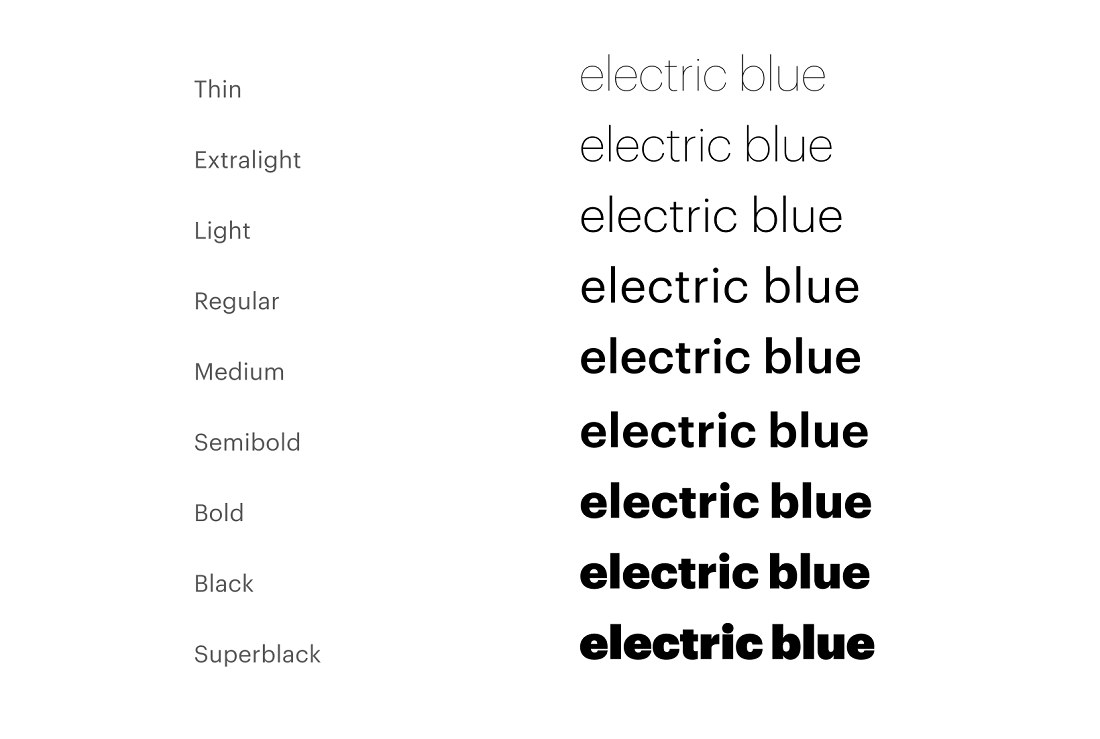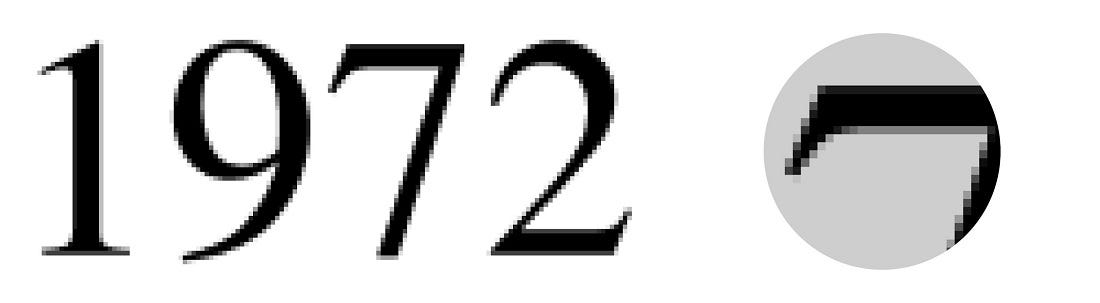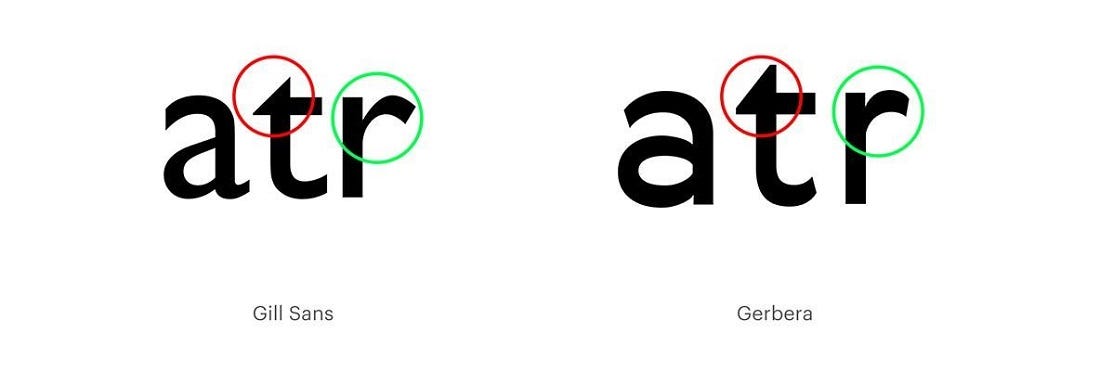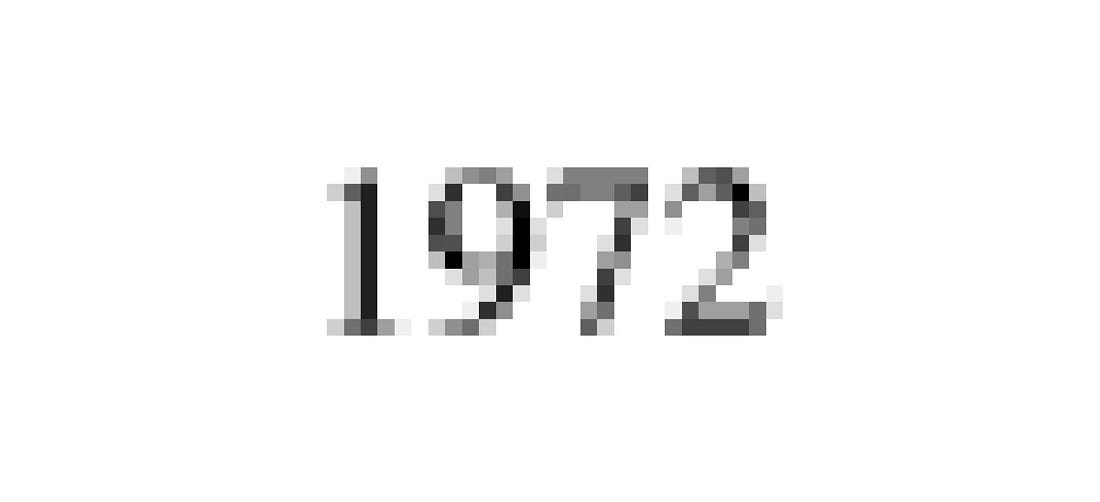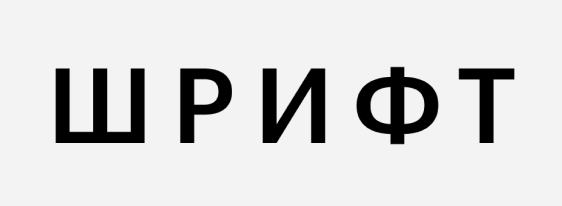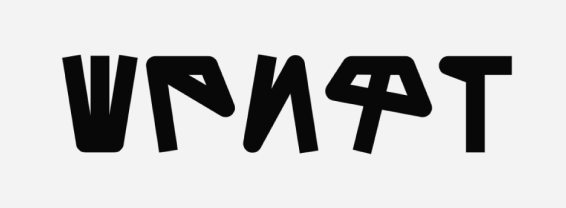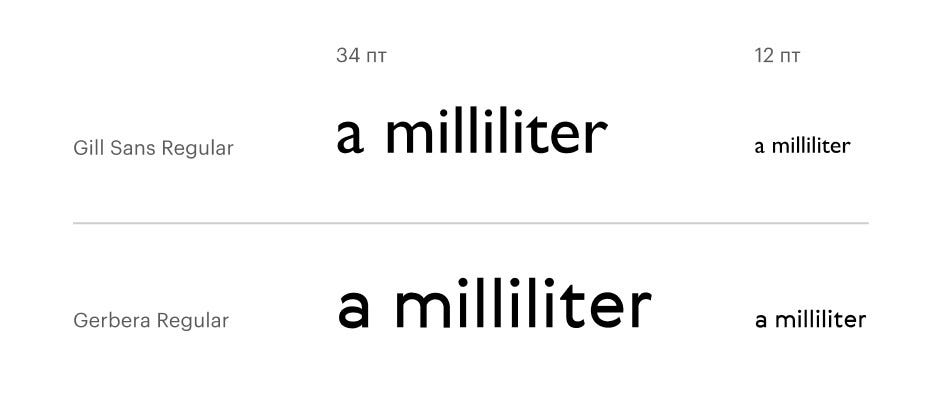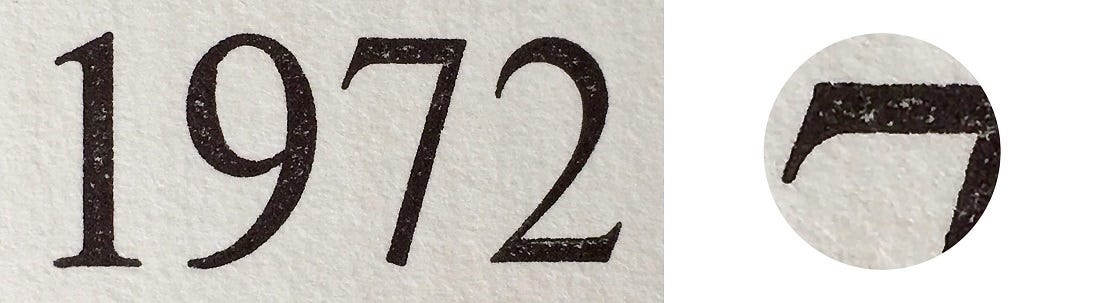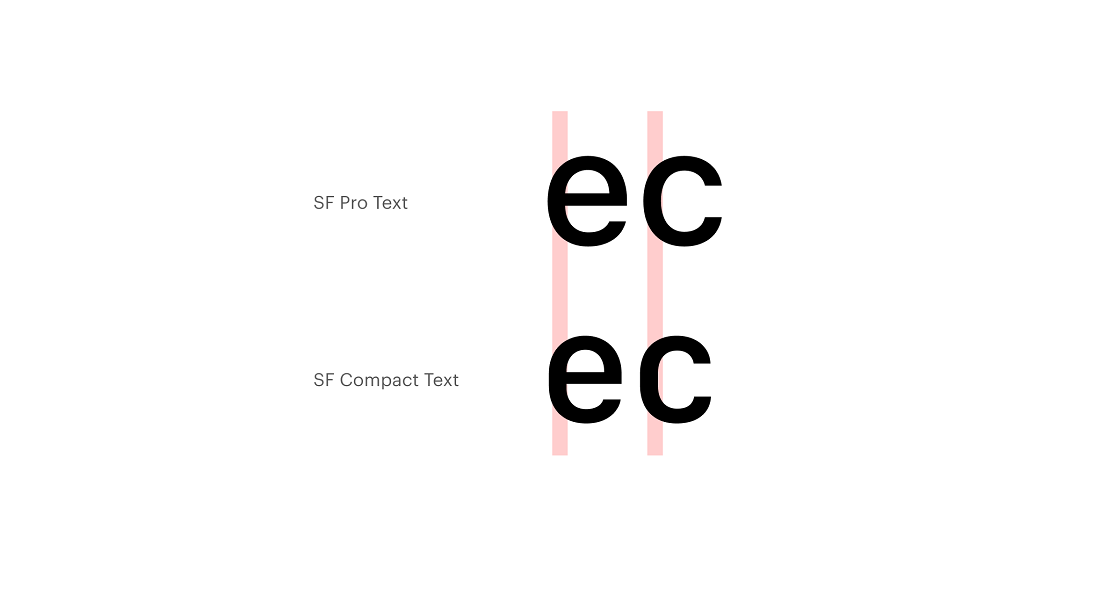
Как правильно выбрать шрифт для диджитал
Шрифт — это удивительное изобретение человека. Являясь, по сути, рисунком букв и знаков, шрифт за всю свою историю последовательно был определен формой пера, затем — отлитым металлическим бруском, а в наше время — сотнями неделимых ячеек, или, говоря проще — пикселями. Шрифт для человека стал чуть ли не частью природы, и поэтому любая его неточность или отклонение от принятого образца кажется странной — настолько мы привыкли к канонам, порой сами того не осознавая.
Посмотрите, как сильно в восприятии отличаются друг от друга два шрифта: весьма нейтральный гротеск Graphik и экспериментальный Potexa от исследователей из Kiosk:
Шрифт Graphik. Commercial Type, type.today
Шрифт Potexa. Kiosk
А теперь представьте, как будет выглядеть длинный текст, набранный Potexa: вряд ли будет просто прочитать пару страниц такой книги. Однако постер, на котором вы увидите крупный заголовок из этих же причудливых букв, будет выглядеть эффектно. Напротив, пара десятков страниц, набранных Graphik, может быть совершенно спокойно прочитана — конечно, если условиться, что это не будет полотном из заглавных букв.
Разные шрифты имеют разное применение, как и в случае с этой парой. Как шрифт для постеров будет нелепо выглядеть в длинных текстах, так и шрифт для чтения может быть плохим выбором для отображения на экранах.
Что такое «шрифт для диджитал»?
Если раньше то, как мы видим и воспринимаем шрифт, зависело от того, как в бумагу впитываются чернила, то сейчас правила устанавливает пиксель — та самая неделимая часть цифрового изображения. Из пикселей собирается всё то, что мы видим на экране, включая буквы, цифры и знаки, и это накладывает определённые ограничения.
Давайте посмотрим на то, как число 1972 в сильном приближении выглядит на бумаге и на экране:
На бумаге
На экране
В обоих случаях у цифр есть свои недостатки. Можно заметить, как несовершенство печати заметно искажает засечку у единицы, а мелкий ворс бумаги делает неровным форму цифры 7. В варианте с экраном видно, как любые непрямые элементы цифр имеют заметную «лесенку», происхождение которой обусловлено построением изображения из квадратных пикселей.
Если мы уменьшим размер шрифта, то результат будет совсем нечитаем:
Уменьшенный размер шрифта. Для наглядности масштаб увеличен
Проблема отображения шрифтов на экране заставила дизайнеров думать о том, как адаптировать существующие и создавать новые шрифты — шрифты для digital.
Так появились всем знакомые Verdana и Tahoma — шрифты, у которых толщина штрихов совпадает с размером пикселя при определённом кегле.
Особенности интерфейсных шрифтов
С развитием технологий размер пикселя становился все меньше, а их плотность — все больше, и проблема «лесенки» начала исчезать. Зато в жизни стали появляться сложные интерфейсы, что создало еще одну проблему для шрифтов — их применение в условиях постоянных ограничений по формату.
UI-дизайнерам прекрасно знакома ситуация, когда в крохотной ширине нужно разместить чуть ли не столько же информации, сколько отображается на целом экране ноутбука. Для того, чтобы удовлетворить столь сложные требования, шрифты для digital выделились в целое направление — интерфейсные шрифты.
Если раньше для большинства задач достаточно было двух видов насыщенности шрифта — нормального, Regular и жирного, Bold, — то сегодня для нас привычно искать в гарнитурах и другие градации: сверхсветлую (Ultra Light), светлую (Light), полужирную (Medium) и другие. Без них интерфейсный шрифт не будет таковым: каждая насыщенность должна закрывать ту или иную задачу.
Заметьте, что в книгах вы не встретите такого обилия разновидностей — они были попросту не нужны. Человеку, который жил на заре печатного дела, даже в голову бы не пришло, зачем нужна насыщенность Medium — ведь есть Regular и Bold.
Насыщенности шрифта Graphik
Одними из самых известных интерфейсных шрифтов являются San Francisco от Apple и Roboto от Google. Эти знакомые всем владельцам iPhone и смартфонам на Android шрифты имеют не только множество начертаний, но и другие особенности, которые делают их по-настоящему интерфейсными.
Возьмем, например, особое начертание San Francisco — Compact, которое было разработано специально для отображения на крохотных экранах Apple Watch.
Сравнение начертаний шрифта San Francisco от Apple
Для удобства чтения с часов — а особенно на ходу или во время пробежки — важно формировать комфортные апроши — расстояния между соседними буквами. Для этого San Francisco Compact обладает более «прямыми» буквами, чем начертание Pro Text. Это сделано для того, чтобы при сравнительно одинаковой длине строки расстояние между буквами было больше у начертания для часов, чем у начертания для других устройств.
Ещё одним наглядным примером будет сравнение культового Gill Sans, который не адаптирован для интерфейсов и схожего с ним по характеру Gerbera от Brownfox. Если в крупном кегле трудностей с чтением у Gill Sans нет, то в маленьком размере явное преимущество у Gerbera.
Делюсь прекрасным и бесплатным интерфейсным шрифтом от ПараТайпа: PT Root UI.
Он имеет одну удивительную особенность: при изменении насыщенности не изменяется длина строки. Это очень удобно при проектировании интерфейсов: дизайнеру не придется перепроверять десятки сверстанных заголовков и текстов, если было принято решение изменить насыщенность.